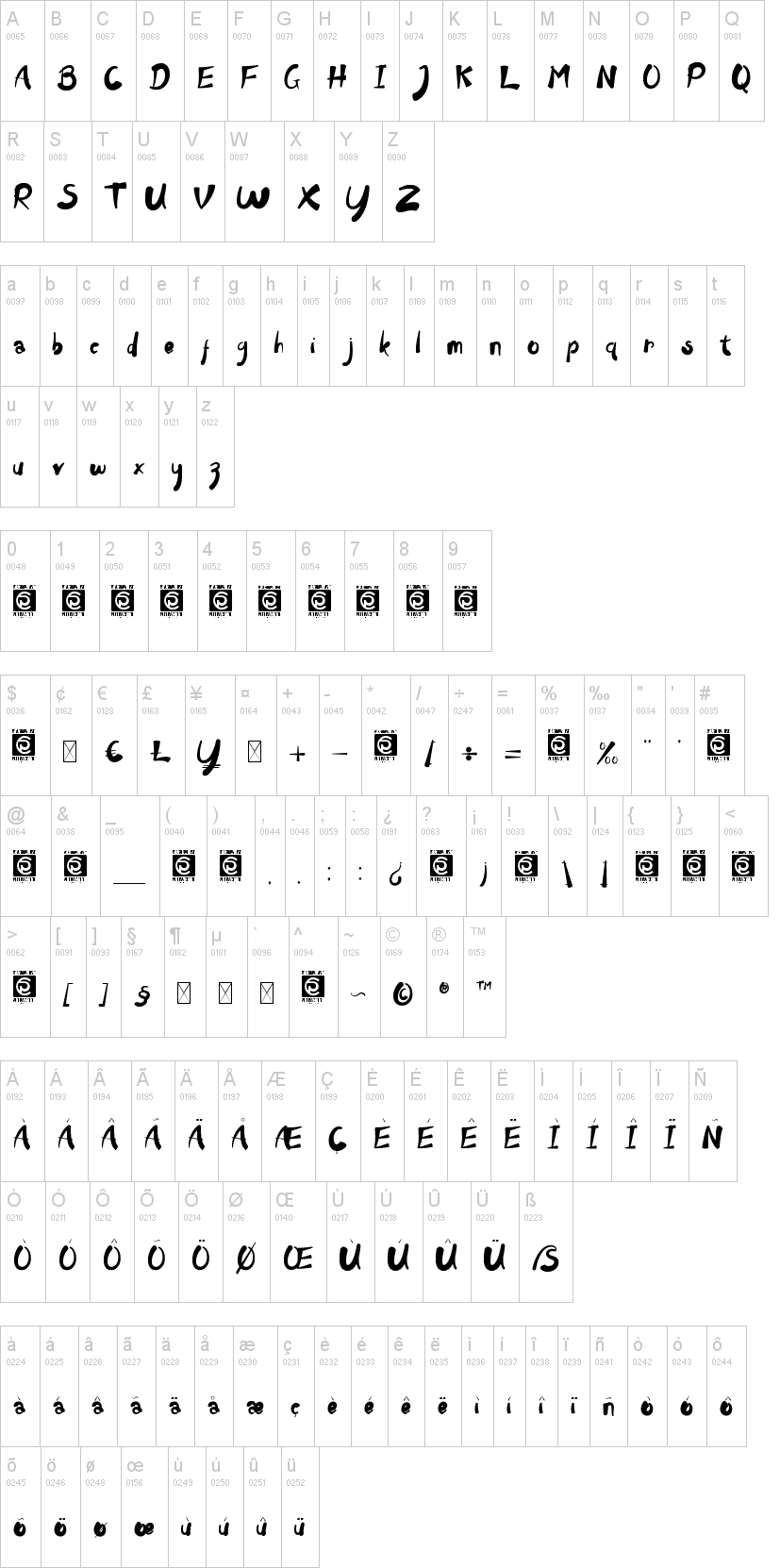
? Clowney 字体是一款由 Fontfabric 公司推出的一款粗犷古朴的复古字体。它具有独特的设计风格,能够为您的设计作品带来更多的创意思维,增加设计的灵活性。Clowney 字体的字体设计采用了一种古典的粗体设计,但它的设计灵感是来自 20 世纪的复古设计,它的字型设计简单而有力,能够很好地表达出您的设计理念。内容介绍
Clowney是一款非常不错的手写艺术字体,具有很好的视觉感,适合于文化类的宣传设计、商业类品牌的广告和产品包装设计以及个性化文字排版等较多场景。